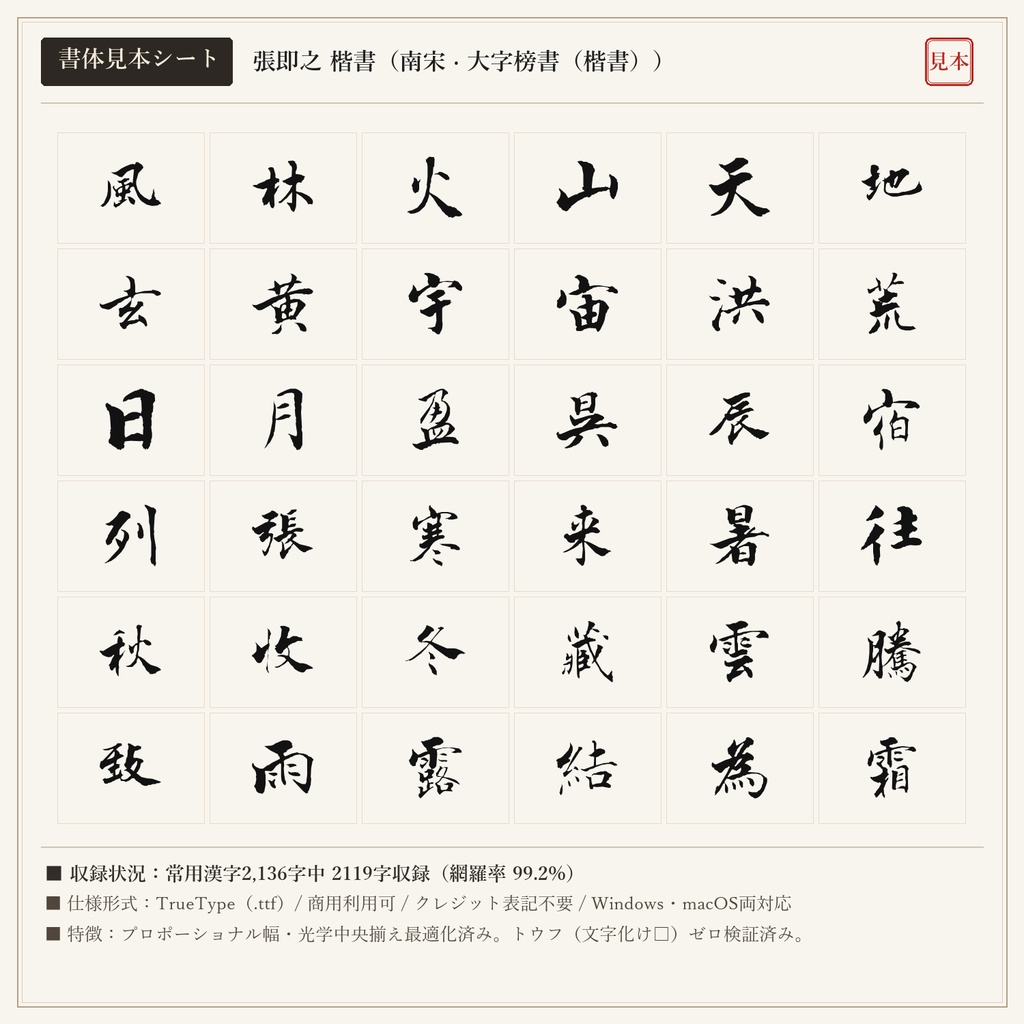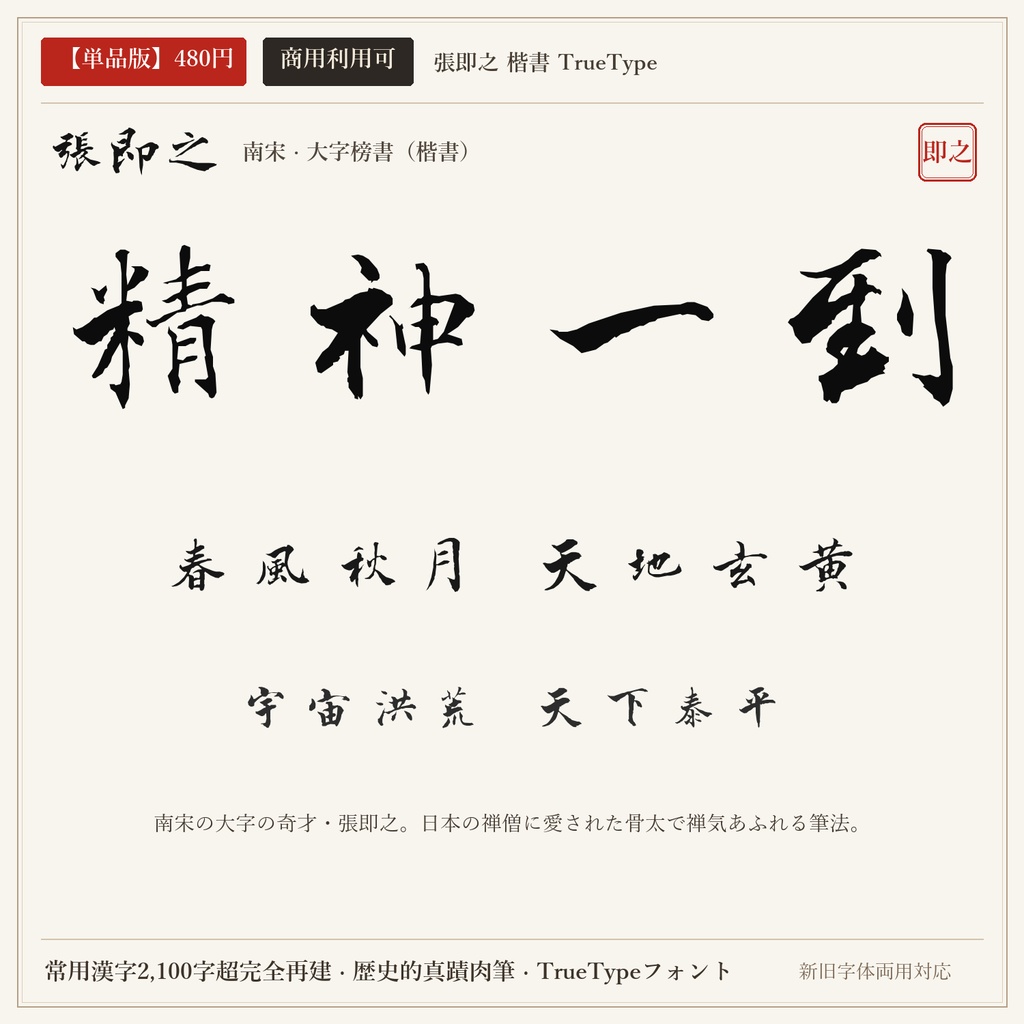
【単品版】張即之 楷書フォント|南宋大字の奇才・禅気漂う筆勢・商用利用可
南宋屈指の能書家・張即之の真蹟墨蹟から輪郭抽出した楷書フォントです。鎌倉時代の禅僧によって日本にもたらされ、禅宗寺院の額字や茶掛けとしても尊ばれた、独特の枯淡と重厚な筆勢が冴え渡ります。 ■ 本フォントの特徴 ・常用漢字2,136字中、2119字を高精度収録(網羅率 99.2%)。 ・現代の新字体を入力しても、歴史的な真蹟字形・旧字体が自然に出力されるデュアルマッピング対応。 ・文字ごとの最適なプロポーショナル字幅設定により、自然で流麗な連綿と墨の息遣いを再現。 ・トウフ(文字化け□)を出さない事前フォントマッピング検証済み。 ■ 未収録文字一覧(全17字) 歴史的真蹟・拓本に存在しない以下の字種は未収録(非対応)となります。ご購入前にご確認ください。 丼 厘 峠 扱 拶 枠 栃 桁 濫 碁 線 脊 著 込 郷 闘 駄 ■ 形式 TrueTypeフォント(TTF) / Windows・macOS両対応 ■ 利用規約 個人・法人の商用利用OK。クレジット表記不要。 ロゴ、動画、ゲーム、書籍、同人誌、配信サムネイル、Web、印刷物、グッズ等に自由にご使用いただけます。 フォントファイル自体の再配布・共有・販売・転売は禁止です。 ※東晋の王羲之(行書)と盛唐の顔真卿(楷書)を同梱した「【無料版】王羲之 + 顔真卿 2書体セット(0円)」もショップ内にて無料配布中です。